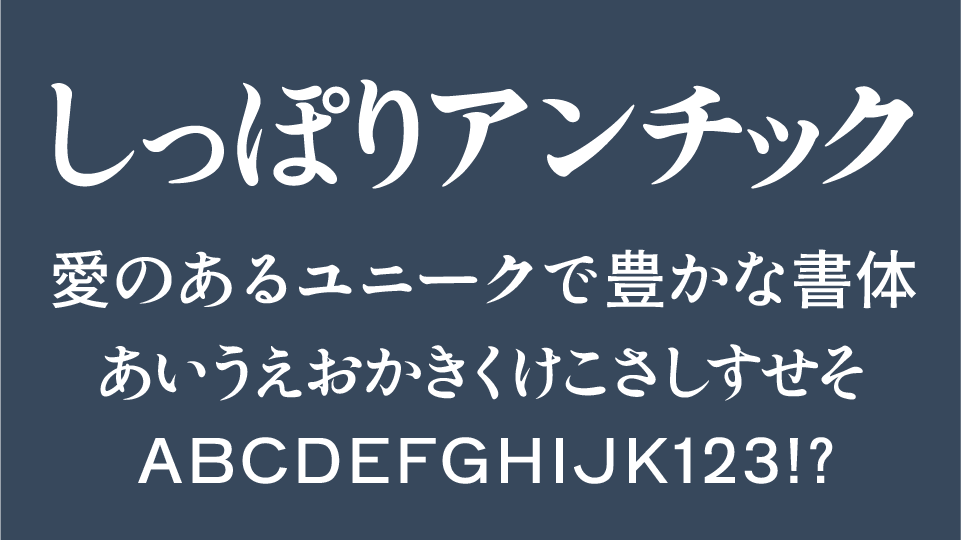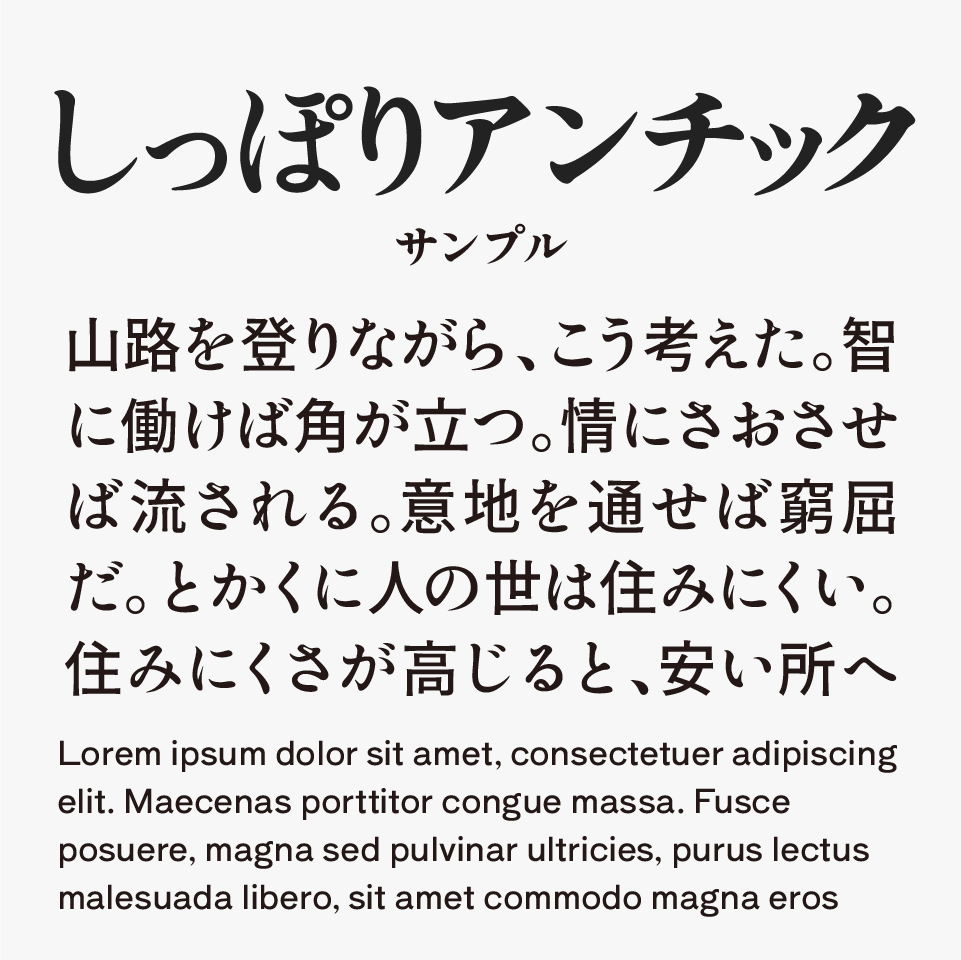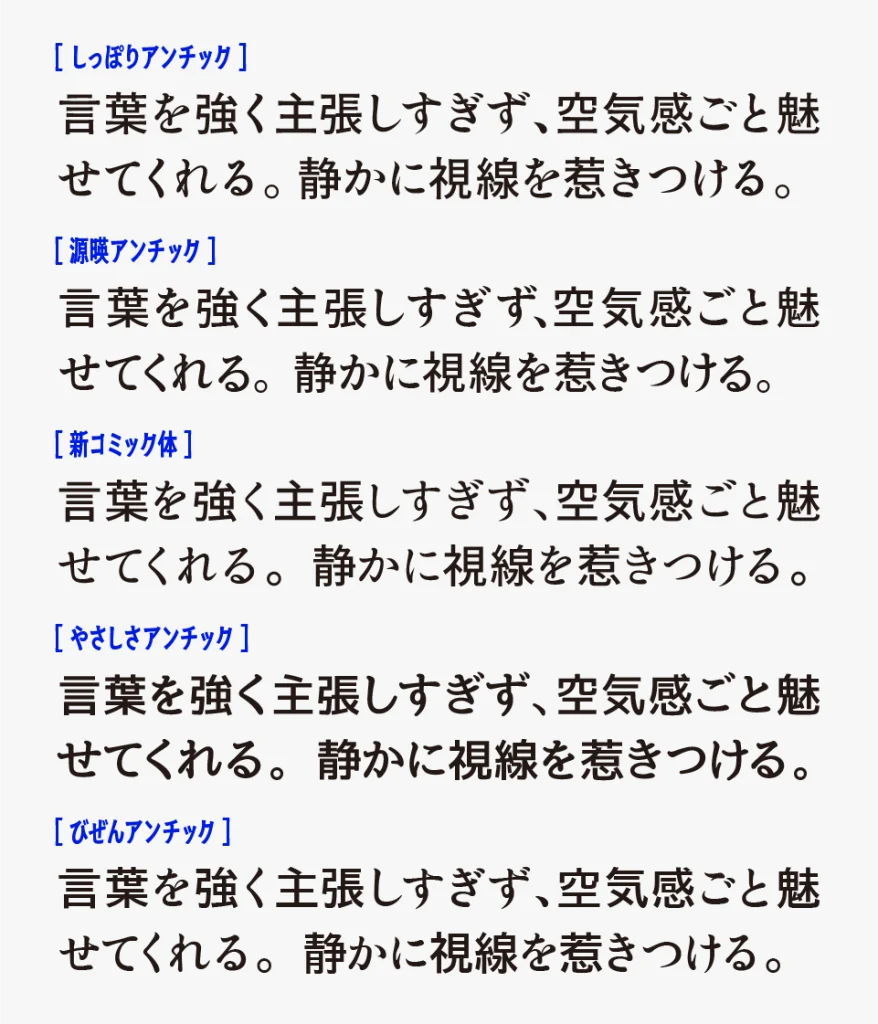
しっぽりアンチック
しっぽりアンチックフォントは、「しっぽり明朝」をベースに、やわらかなかな文字と「源石ゴシック」の漢字を組み合わせて制作されたアンチックフォントです。
明朝らしい上品さを残しながらも、読みやすさと親しみやすさが加わっており、コミックや漫画のセリフ、吹き出しなどにも使いやすい雰囲気に仕上がっています。
やさしく落ち着いた空気感があるため、感情表現のある会話シーンや、少し文学的な世界観の作品とも相性の良いフォントです。
筆文字感のある明朝体に、可読性が優れているゴシックを組み合わせた正統派アンチック体です。アンチックフォントを探されている方には「しっぽりアンチック」おすすめです。
マンガ吹き出しでも、ある程度小さいサイズ感になっても視認性・可読性が優れているアンチックフォントとなっています。
マンガの吹き出し内でも、小さめのサイズになった際の視認性・可読性に優れており、セリフが詰まったシーンでも読みやすさを保ちやすいアンチックフォントとなっています。
一般的なアンチックフォントと比べると、やわらかく印象がありながらも、文字の輪郭がつぶれにくいので、長文でも目が滑りにくいところが特徴です。
用途にあわせて使い分けるのもおすすめなので、ぜひ比較しながらチェックしてみてください。(源暎アンチック、新コミック体、やさしさアンチック、びぜんアンチック)
収録文字は、ひらがな・カタカナ・漢字・記号・英数字が収録されているとのことです。